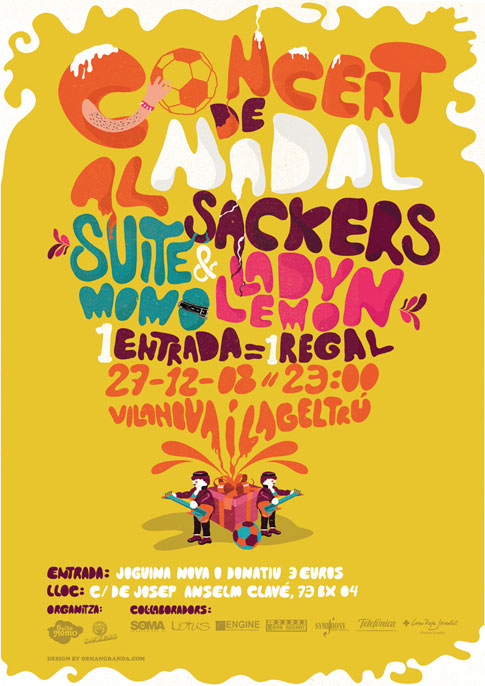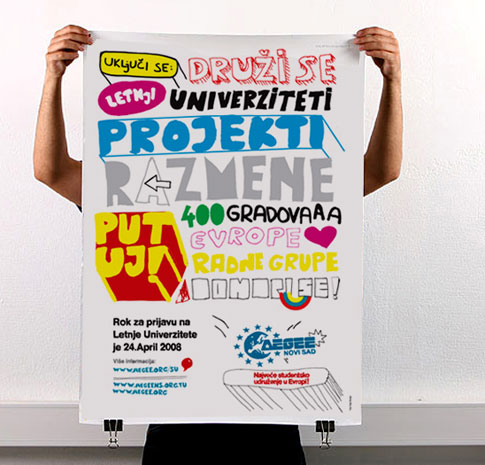
17 grupos de flickr inspirados por tipografias
Diana de artegami publico sbre un post de bitbox que ha recopilado 17 grupos de flickr inspirados por tipografías, todos estos grupos de diseñadores han trepado al servicio de hospedaje de fotos de yahoo un sin numero de diseños de carteles y banners basados en tipografías, logrando excelente diseños con pocas imagenes y muchas letras estelizadas.
Muy interesantes las galerias, aquí les dejo enlaces a algunos grupos de flickr, si quieren conocer todas solo sigan el enlace al final.